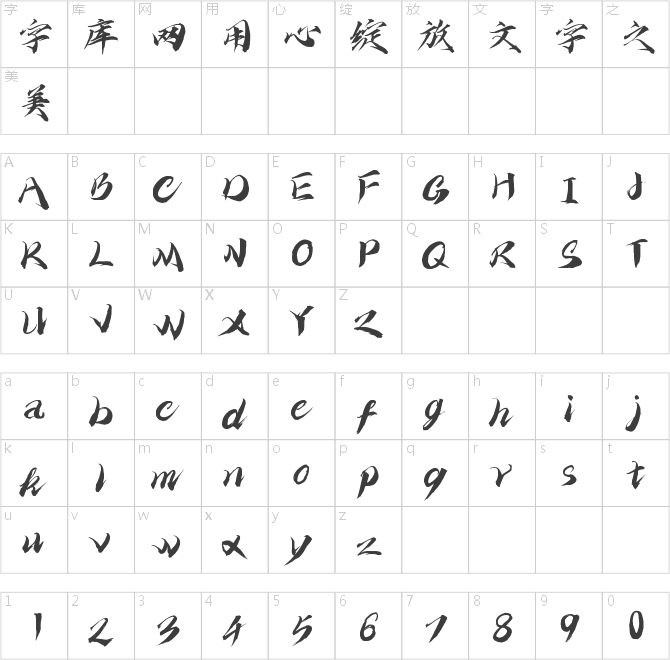
iSlide云犹体
iSlide&iFonts联合推出独家毛笔字体免费商用
iSlide云犹体在秀丽毛笔字风格的基础上更加强调了字体的曲折收放变化,使得整个字体开合揖让有度,辗转腾挪,不至过于秀气婉约,婉转中铿锵有力,锋芒外露。
iSlide云犹体局部的形变与外拓带来的是整体气势的叠加,兼顾了阴柔与阳刚、含蓄与强劲。露锋用笔贯彻到了字体的始终,结体紧致,大量的曲线强化了字体的动感与字形张力。